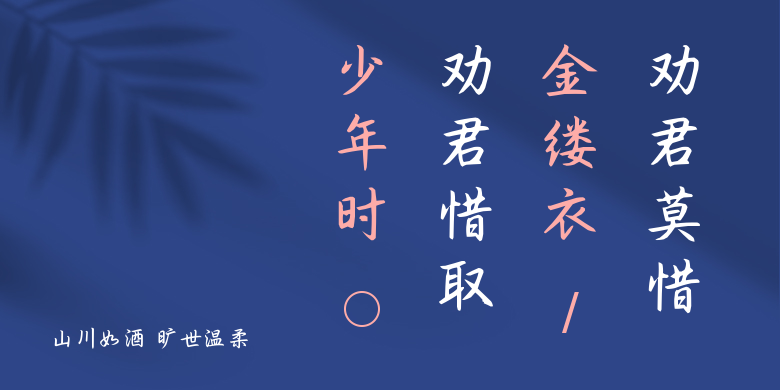
山川如酒 旷世温柔
山川如酒 旷世温柔,这款字体结构工整、笔画清晰,兼顾美观与易读性,适用于标题、正文、海报、包装、LOGO 等多种场景。字形优雅稳定,风格百搭耐看,适配日常排版与创意设计,让文字呈现更舒适、更具质感。山川如酒 旷世温柔一笔一画,皆是细节,以均衡的比例、流畅的线条打造舒适视觉体验,字形端正大气,风格简约现代。无论是商业设计、品牌宣传还是日常排版,都能轻松驾驭,让文字更有格调与力量。山川如酒 旷世温柔字体下载。